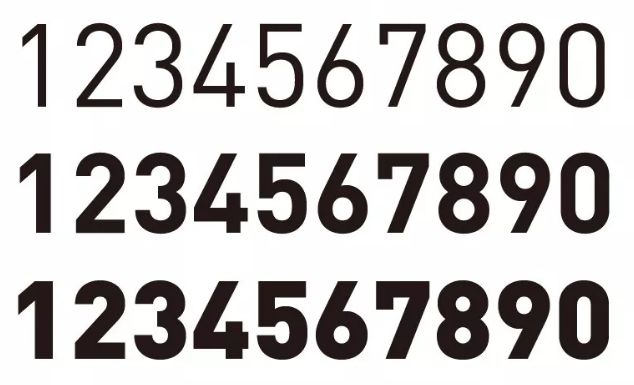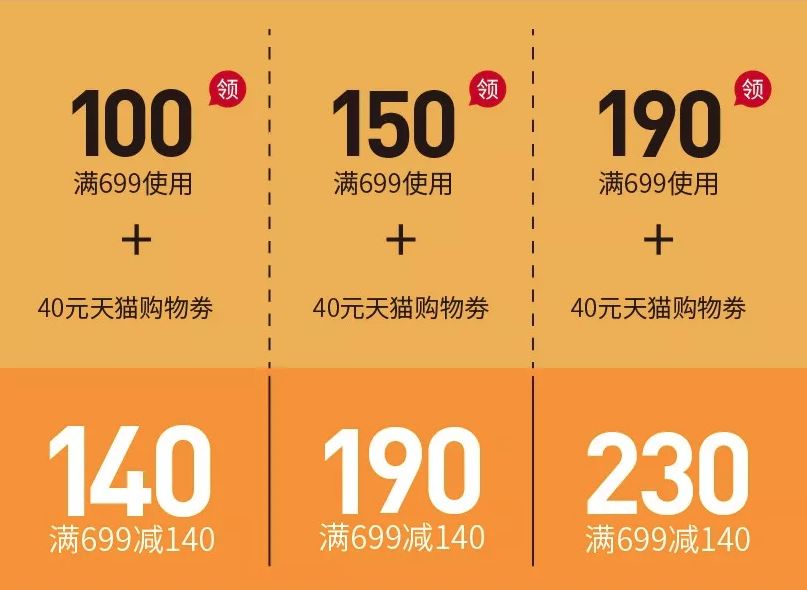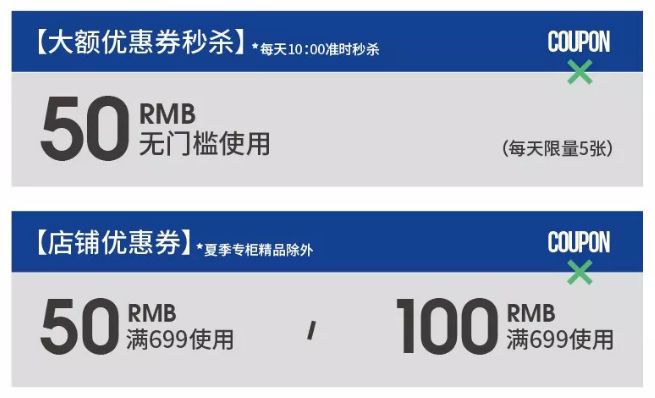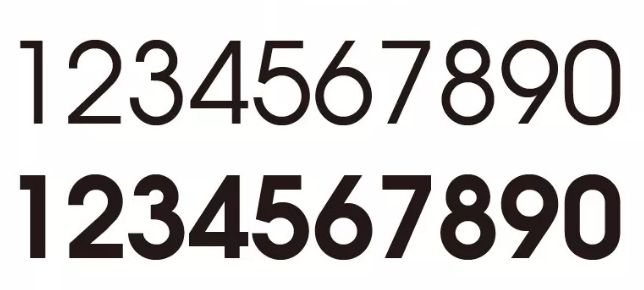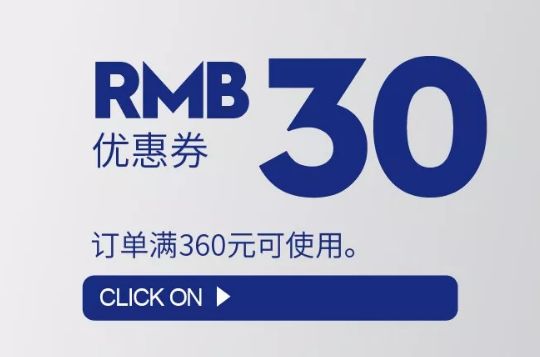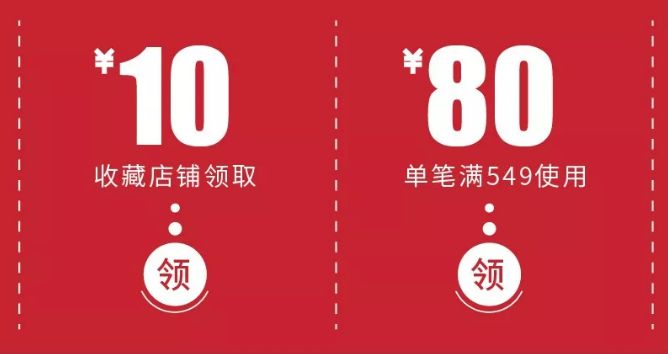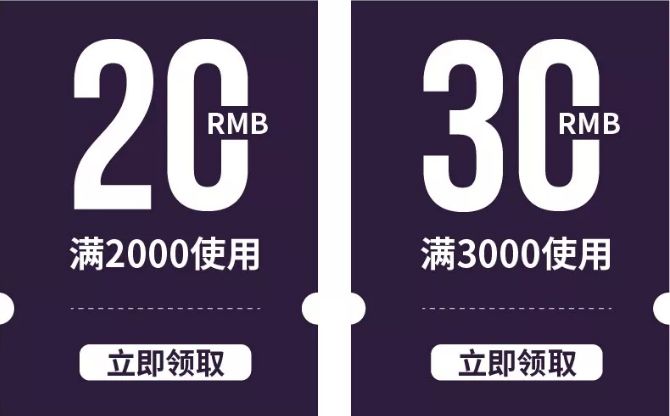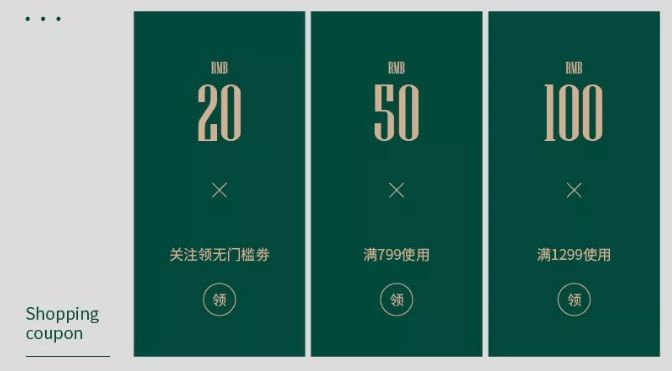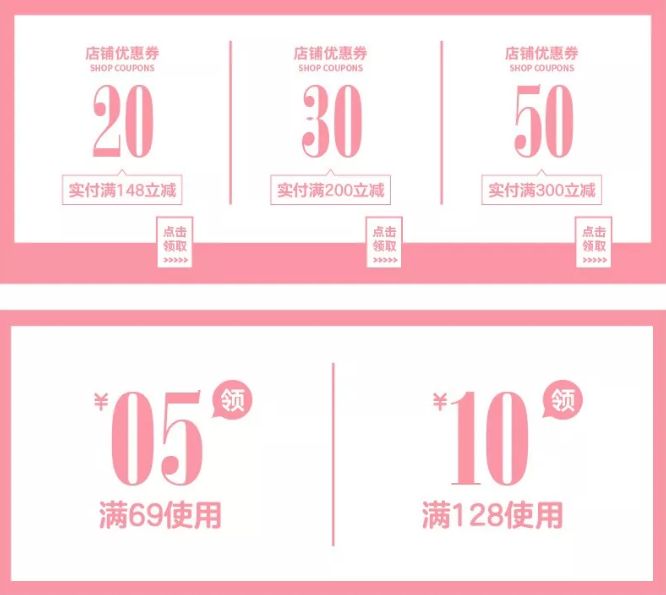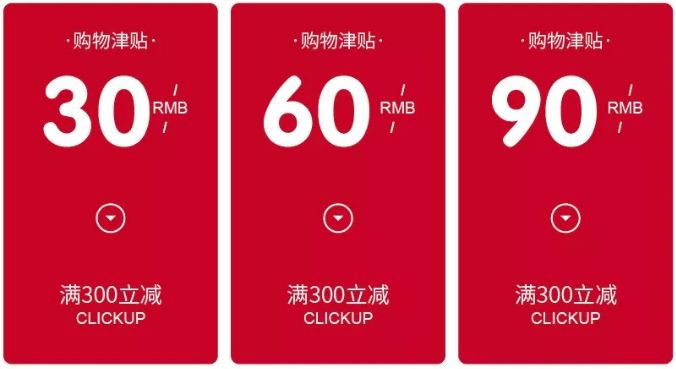
电商设计行业已经逐渐成熟了,除了设计牛逼的详情页面,美工还要学会运用数字,优惠的价格加上吸引人的数字魅力,下单付款那是分分钟的事情。很多朋友不会运用价格字体,往往执着详情版式设计,忽略了海报图上的价格字体,是时候注意这些小细节了。
DIN 字体
欧洲最大的专业字体设计公司 fontshop 公布的世界上 100 个最佳字体中 DIN 排名第 20 。
Avanti 字体
Tensans 字体
Impact 字体
BEBAS 字体
Niagara 字体
ArsisDReg 字体
Rotondac 字体
027-CAI978 字体